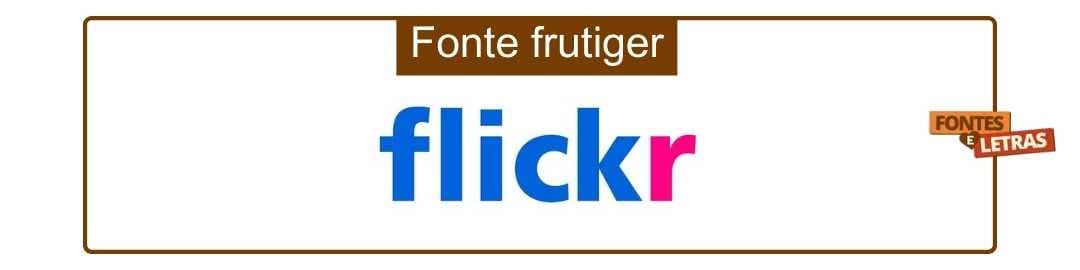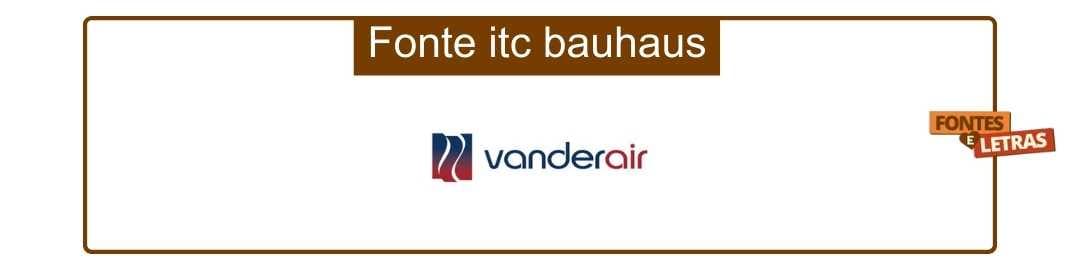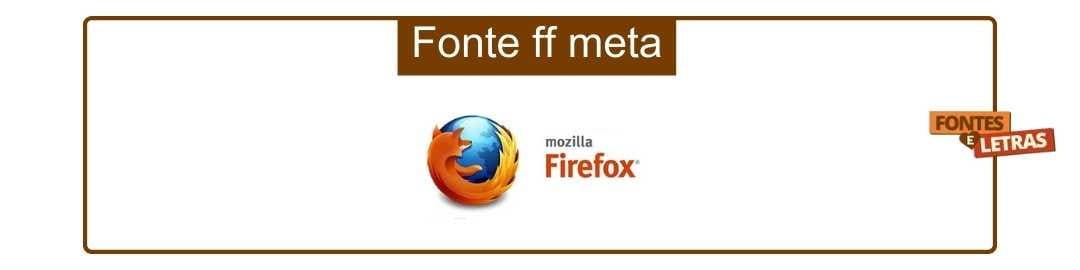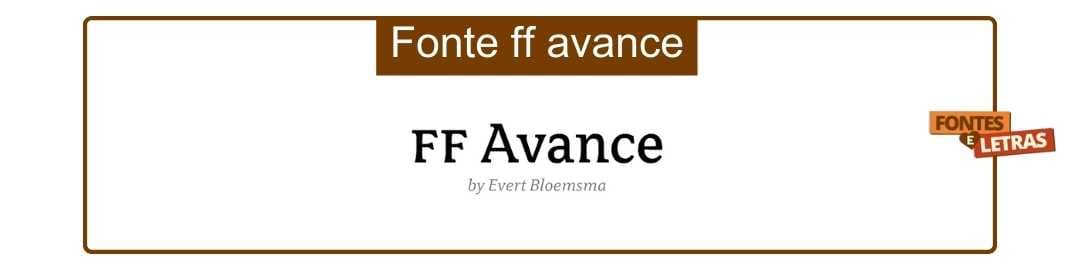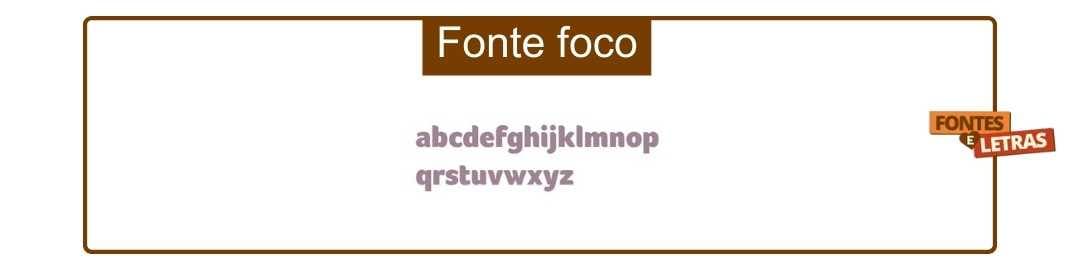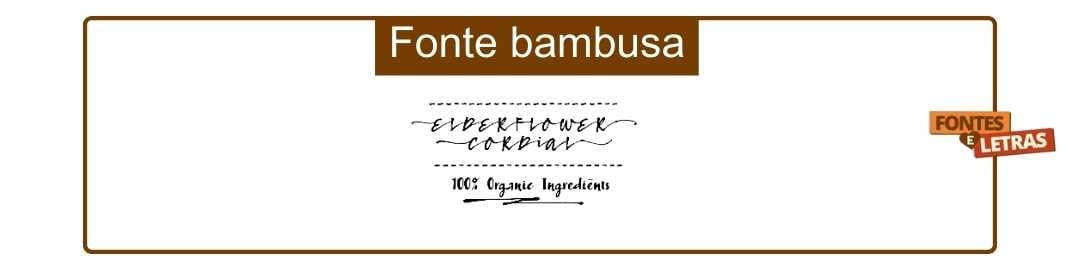
50 logotipos de fontes que você deve conhecer
Geralmente pensamos em cores e imagens no design gráfico, especialmente em logotipos. Mas os logotipos com fontes são elementos essenciais de design. Na verdade, muitos logotipos icônicos de empresas são baseados em tipografia. Se um logotipo tiver um nome de marca, o sucesso de seu design dependerá do uso habilidoso das fontes.
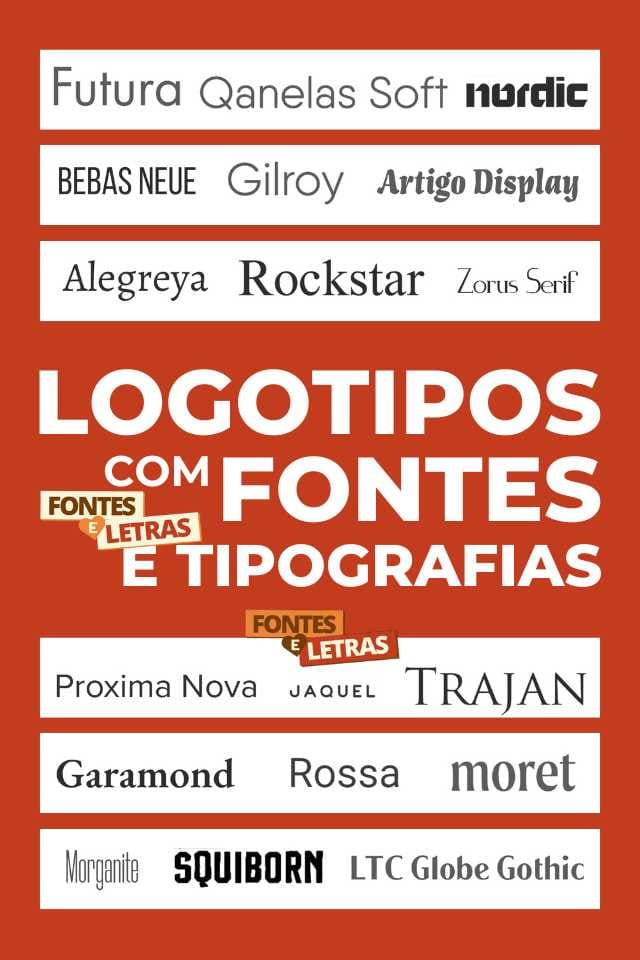
Felizmente, há uma grande variedade de fontes disponíveis para fazer a escolha certa. Somente um designer gráfico habilidoso e experiente pode incorporar uma fonte tão perfeita em um design. Um designer habilidoso sabe como dar uma forma diferente a uma fonte convencional e pode criar um design exclusivo.
Por exemplo, muitos logotipos deram uma nova aparência às letras clássicas. O logotipo da Coca-Cola é um dos melhores exemplos de como as letras podem criar uma identidade de marca. O logotipo da sua empresa é baseado em tipografia? Se for, dê uma olhada e descubra se ele usa o poder da tipografia corretamente.
Certifique-se de que as fontes usadas no logotipo da sua empresa estejam em sincronia com a personalidade da sua marca uma boa fonte faz toda a diferença! A fonte do logotipo desempenha um papel crucial na criação da imagem da empresa. Acredite ou não, a fonte de seu logotipo conta a história de sua marca antes mesmo de suas palavras.
A escolha da fonte pode ser decisiva para o design do seu logotipo. Porém, com tantas fontes na Internet, pode ser difícil para um designer selecionar a fonte certa. Entretanto, há algumas fontes que os designers devem ter em sua coleção para causar a primeira impressão.
Fizemos uma lista das fontes tipográficas mais populares para designers. Essas belas fontes para títulos e textos são as mais repetidas em projetos gráficos:
Cabin
Lato
Open Sans
Montserrat
Futura
PT Sans
Garamond
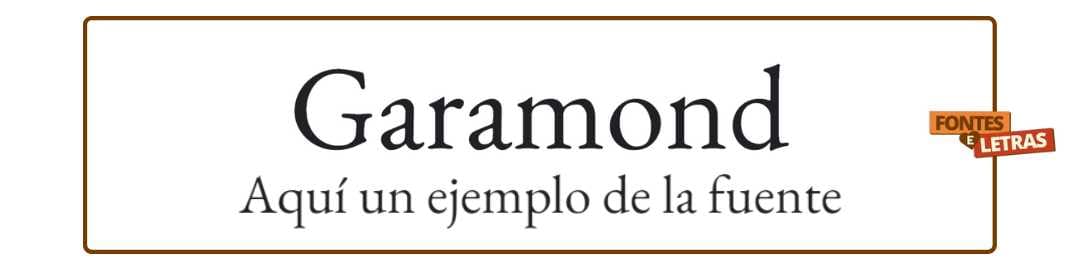
Droid Sans / Serif
Caslon
Arvo
League Gothic
Patua One
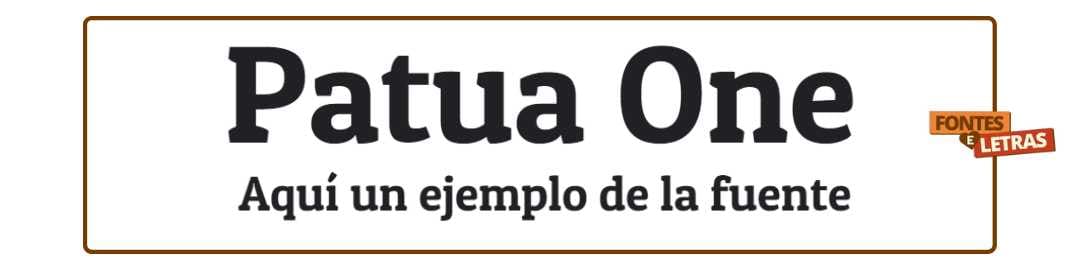
Cookie
Vollkorn
Varela Round
Baskerville
¿Cuáles letras son las más usadas para chamar a atenção?
Toda a família de letras Sans Serif, ou góticas, são muito utilizadas em redes sociais e publicidade, pois são fáceis de visualizar e entender. Otras muy comunes son: Arial, Verdana, Calibri, Tahoma, Helvetica, Lucinda Grande y Trebuchet.
50 logotipos com fontes que todo designer deve conhecer
01. Garamond
Esta não é uma única fonte, mas uma família de fontes serifadas antigas. Essa fonte tem excelente legibilidade e é elegante. As diferentes fontes incluem Adobe Garamond, Stempel Garamond, EB Garamond, Sabon Next e ITC Garamond. Ela é normalmente usada em revistas, sites, livros didáticos e corpos de texto longos. Uma publicação alemã classificou essa fonte como a segunda melhor de todas as fontes tipográficas. A fonte foi lançada pela primeira vez em 1989.
02. Helvetica
A Helvetica é uma das fontes mais usadas em uma variedade de designs gráficos. Os profissionais gostam especialmente dessa fonte. A Helvetica foi incluída nos computadores pessoais desde 1984 e esse é um dos motivos de sua popularidade. Muitos profissionais gostam e não gostam dessa fonte por um simples motivo: as letras dessa fonte são muito espaçadas. Porém, a seleção cuidadosa da fonte é necessária para um design de logotipo eficaz. Essa fonte não pode ser usada em todos os lugares para enviar a mensagem desejada.
03. Trajan
A Trajan tem sido usada há muito tempo em pôsteres de filmes de Hollywood. A fonte também é a favorita de muitos designers que precisam criar designs relacionados a leis, casamentos, religião e coisas do passado. Trajan é uma fonte serifada de estilo antigo e foi projetada por Carol Twombly em 1989. O design da fonte é baseado em letras maiúsculas quadradas romanas. Essa fonte garantirá a versatilidade do design de seu logotipo.
04. Futura
A Futura é conhecida por seus círculos, quadrados e triângulos quase perfeitos, pois é baseada em formas geométricas. Devido à sua forma geométrica exclusiva, essa fonte é usada com frequência em telas grandes, designs corporativos, livros e logotipos. A fonte é considerada por muitos como ideal para textos pequenos.
05. Bodoni
Se estiver procurando uma fonte ideal para títulos, logotipos e textos decorativos, a Bodoni pode ser sua melhor opção. Ela tem serifas planas e sem restrições e uma estrutura subjacente estreita. Há traços grossos e finos nessa fonte e há um contraste entre os dois. A fonte tem uma aparência esteticamente agradável devido à sua construção geométrica. Não se esqueça de mencionar essa fonte especialmente em seu briefing de design ao terceirizar seu trabalho de design.
Muitos dos grandes tipos de fontes são acessíveis aos designers gráficos. Eles devem escolher uma fonte que possa expressar a personalidade da marca de uma empresa. Mas a escolha da fonte certa pode ser complicada, pois muitos aspectos da empresa do cliente precisam ser mantidos.